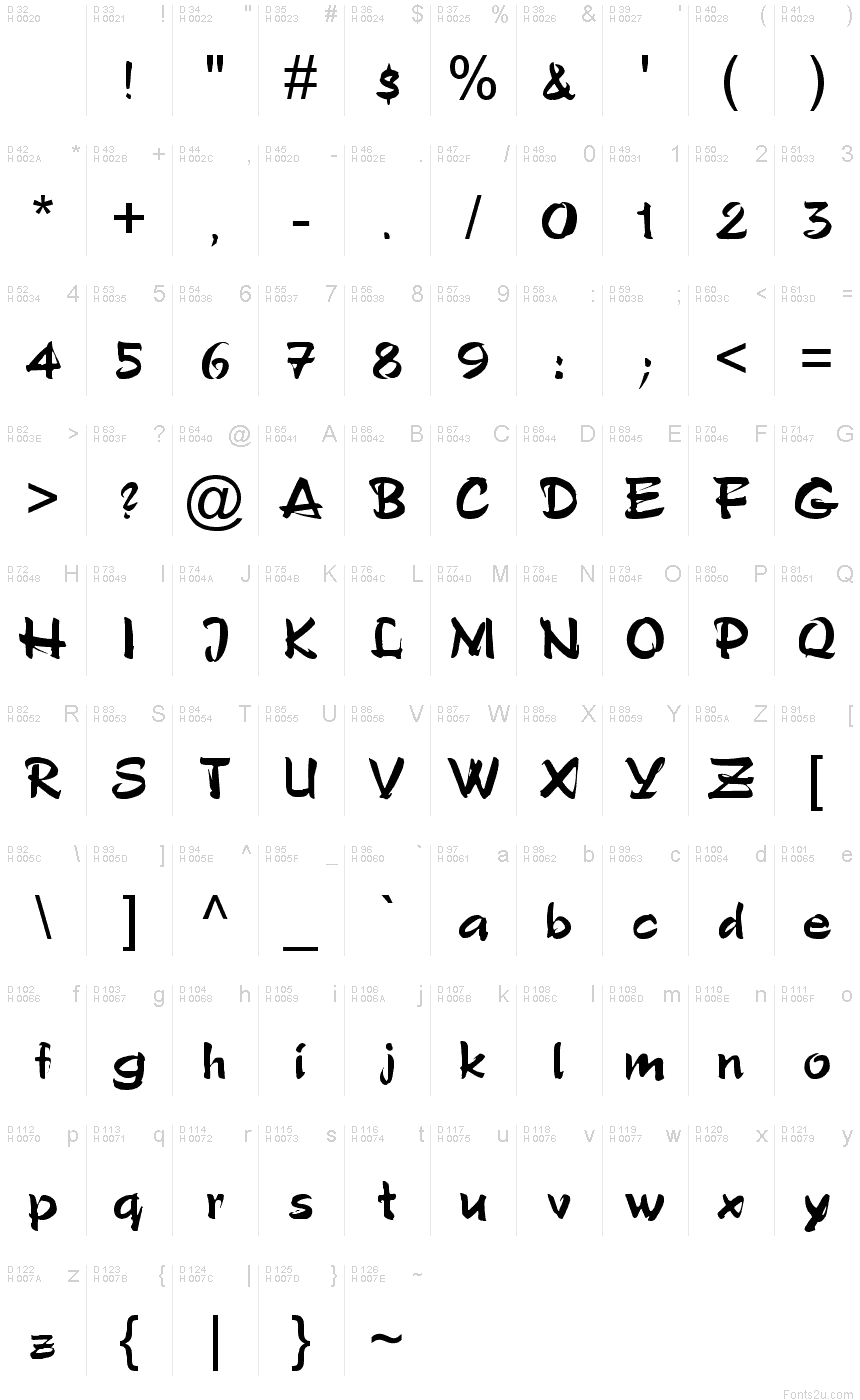
VPS Dong Da 字体
VPS Dong Da 字体家族,包含 2 款字体
VPS Dong Da
VPS Font 推出的 VPS Dong Da 是一款免费的越南语笔刷展示字体,带有生动的纯手绘感。字母在宽阔圆润的笔触和尖锐的钩状末端之间自由摆动,形成了一种节日的、民俗的风味,比起整洁的书法,它更像是在手绘招牌上的感觉。
它非常适合用于海报标题、咖啡馆品牌设计、活动传单、包装和标题卡,当您需要一款具有强烈本土风情且不会显得生硬的免费字体时,它是理想之选。由于其造型依赖于大胆的曲线和细小的渐收笔触,它也非常适合用于需要动感和一丝街头魅力的短篇封面文案或类字母组合(monogram)的首字母设计。